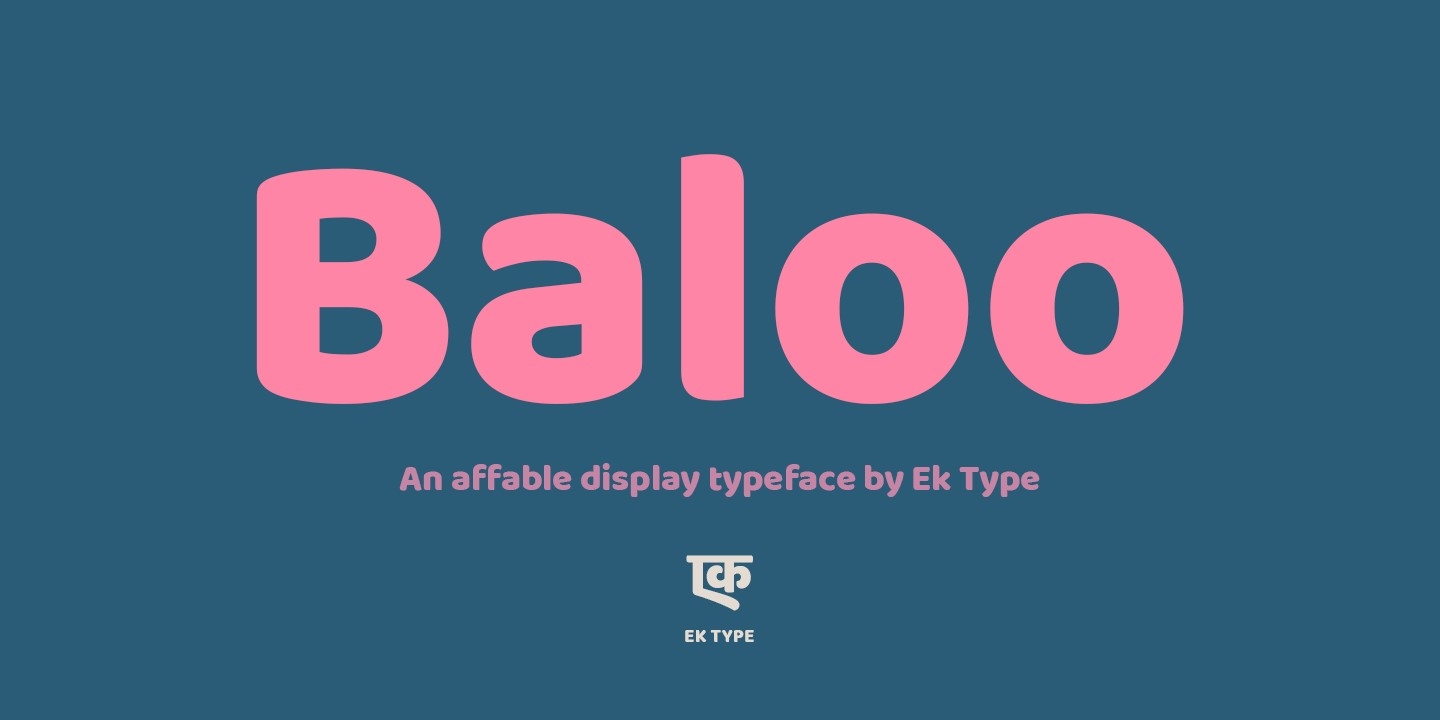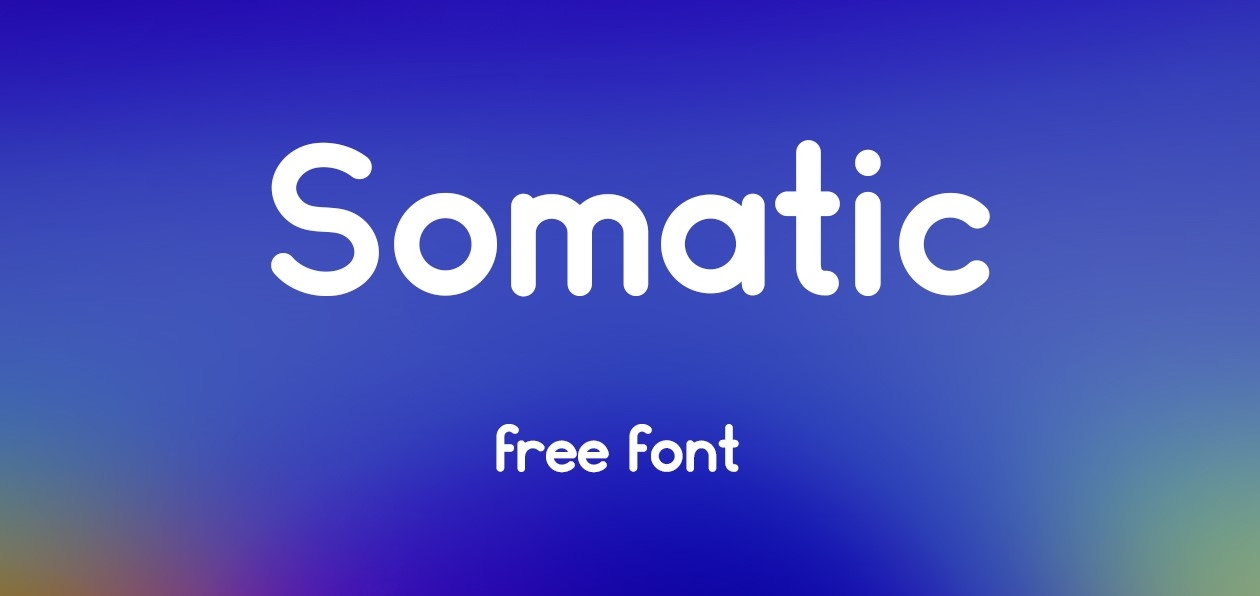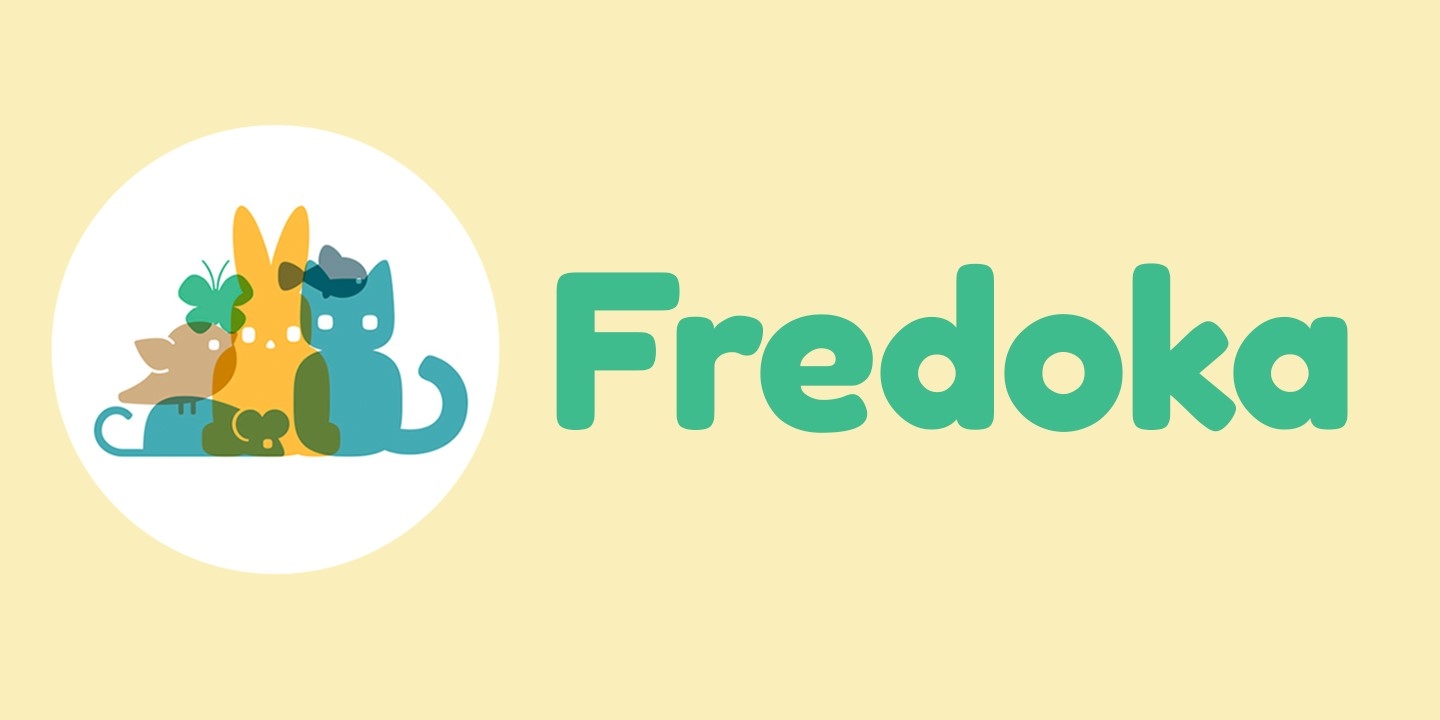
Tổng hợp TOP 15 font chữ tròn sinh động, sáng tạo, thiết kế đẹp mắt và ấn tượng
Các font chữ tròn với đường nét mềm mại, sinh động và sáng tạo luôn là lựa chọn hàng đầu của nhiều ấn phẩm thiết kế. Nhờ sở hữu vẻ đẹp gần gũi, vui tươi mà font chữ tròn luôn hút mắt người xem. Trong bài viết này, FPT Shop đã tổng hợp 15 font chữ tròn ấn tượng hiện nay, mời bạn cùng theo dõi nhé!
1. Baloo - Font chữ tròn miễn phí
Baloo nổi tiếng là một trong những font chữ tròn đẹp nhất dành cho dân thiết kế. Điểm thu hút của Baloo chính là những nét chữ tròn đáng yêu, ấn tượng với nhiều font family khác nhau, đáp ứng mọi nhu cầu sáng tạo.
Không chỉ được ưa chuộng tại Việt Nam, Baloo còn được sử dụng rộng rãi trên toàn thế giới. Font chữ này hỗ trợ đa dạng ngôn ngữ, bao gồm cả tiếng Việt và cho phép miễn phí sử dụng. Bạn có thể tải font Baloo ngay để thỏa sức sáng tạo mà không sợ bị lỗi font.
Baloo thích hợp với nhiều dự án thiết kế từ đơn giản đến phức tạp, chẳng hạn như: poster, logo, banner, website, danh thiếp, thiệp mời, bìa sách, bài đăng trên các phương tiện truyền thông xã hội và hơn thế nữa.
2. Somatic - Font chữ tròn hiện đại
Font chữ Somatic thu hút người dùng bởi những đường nét tròn trịa, mềm mại, tạo cảm giác vui tươi và đáng yêu. Đặc biệt, khi kết hợp với hiệu ứng gradient, Somatic càng trở nên nổi bật và ấn tượng hơn.
Nếu để ý kỹ hơn, bạn sẽ thấy Somatic sở hữu phong cách tương đồng với font chữ mà thương hiệu Apple sử dụng trong các sự kiện ra mắt sản phẩm đình đám.
Somatic sẽ là lựa chọn tuyệt vời cho những ai yêu thích phong cách trẻ trung, hiện đại và muốn tạo điểm nhấn ấn tượng cho thiết kế của mình. Hiện tại Somatic đang phát hành miễn phí cho tất cả người dùng và được đông đảo designer tin tưởng lựa chọn.
3. Fredoka - Font chữ tròn đẹp
Font chữ Fredoka thu hút bởi những đường nét bo tròn mềm mại, tạo cảm giác nhẹ nhàng và thanh thoát. Tuy là font chữ tròn nhưng Fredoka không quá to ngang nên dễ đọc, có khả năng hiển thị tốt và dễ dàng ứng dụng trong thiết kế.
Font Fredoka được nhiều designer ưa chuộng sử dụng cho các thiết kế trên website, phần mềm và các nền tảng trực tuyến. Font chữ này có thể tải về miễn phí từ Google Fonts.
4. Softa - Font chữ béo ngộ nghĩnh 3D
Được lấy cảm hứng từ những viên kẹo marshmallow bông xốp nên font chữ Softa sở hữu đường nét tròn trịa, mềm mại, kết hợp với hiệu ứng 3D độc đáo mang đến cảm giác vui tươi và tinh nghịch. Font chữ này cũng được tích hợp sẵn hiệu ứng đổ bóng mặc định cực kỳ thu hút và bắt mắt.
Softa thích hợp với các thiết kế mang tính sáng tạo như: logo, banner, poster, thiệp chúc mừng,... Đồng thời, font chữ cũng hỗ trợ nhiều định dạng khác nhau và tương thích với các phần mềm thiết kế. Bạn có thể tải và sử dụng font chữ Softa miễn phí cho mục đích cá nhân.
5. Yikes - Font chữ tròn tinh nghịch
Font chữ Yikes là một lựa chọn tuyệt vời cho những kiểu thiết kế mới lạ, tinh nghịch và ngộ nghĩnh. Với các đường nét tròn trịa và mềm mại, Yikes mang đến cảm giác thân thiện và dễ thương. Ngoài ra, font chữ Yikes cũng được thiết kế với độ phân giải cao, hiển thị sắc nét và đẹp mắt trên mọi thiết bị.
Font chữ Yikes đang được phát hành hoàn toàn miễn phí, cho phép người dùng sử dụng thoải mái trong các dự án cá nhân và thương mại. Hiện tại, Yikes đã được Việt hóa 100% nên bạn có thể tha hồ sử dụng mà không sợ bị lỗi font.
6. Earth Days Swash - Font chữ tròn béo hoa lá cành
Earth Days Swash là font chữ tròn béo mang đậm phong cách thiên nhiên với các họa tiết hoa lá cành ẩn chứa trong từng chữ cái. Font chữ này là lựa chọn hoàn hảo cho các thiết kế hướng đến trẻ em, các ấn phẩm về môi trường hoặc bất kỳ dự án nào muốn mang đến cảm giác tươi mới, gần gũi với thiên nhiên.
Earth Days Swash hỗ trợ nhiều ngôn ngữ và dễ dàng cài đặt trên các phần mềm thiết kế phổ biến. Đặc biệt, font chữ này đã được Việt hóa nên bạn có thể thoải mái sử dụng mà không lo lỗi font.
Tuy nhiên, bạn cần lưu ý font chữ này chỉ được sử dụng miễn phí cho mục đích cá nhân. Nếu muốn sử dụng cho mục đích thương mại thì bạn cần mua bản quyền gốc từ tác giả.
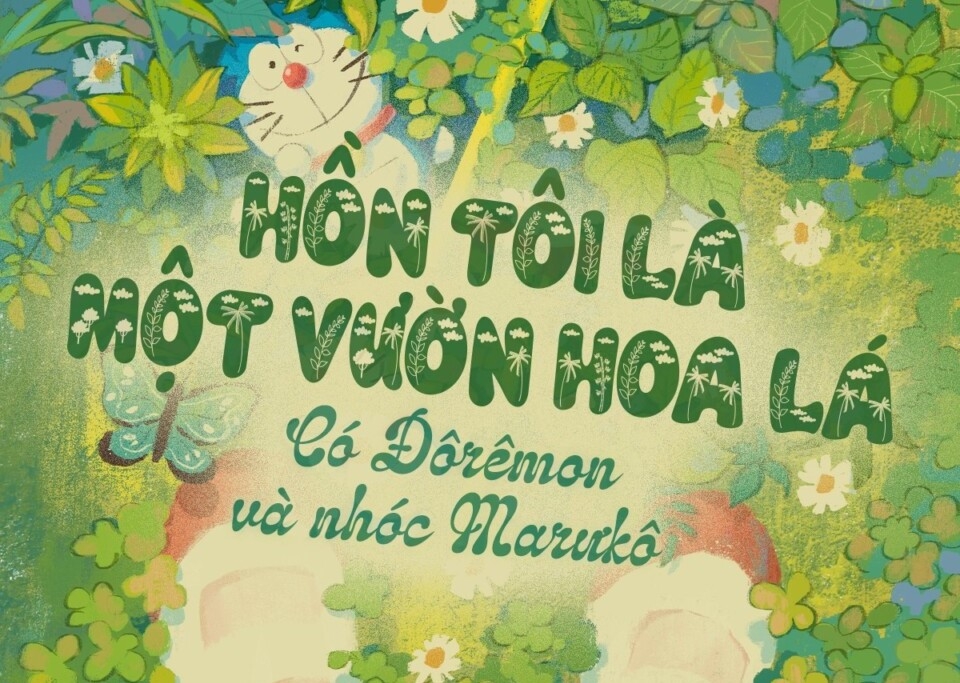
7. Alba Matter - Font chữ tròn vừa hoài cổ, vừa hiện đại
Alba Matter là font chữ tròn sở hữu vẻ đẹp hoài cổ xen lẫn hiện đại. Font chữ này đem lại cảm giác mộc mạc nhưng vẫn đầy tinh tế, phù hợp với các thiết kế mang phong cách vintage, retro hoặc muốn tạo điểm nhấn độc đáo.
Font Alba Matter đã được Việt hóa để người dùng có thể sử dụng tiếng Việt trong thiết kế một cách dễ dàng. Font này vô cùng lý tưởng cho các mẫu logo, poster cho quán ăn, tiệm cà phê, đồ thủ công, du lịch,...
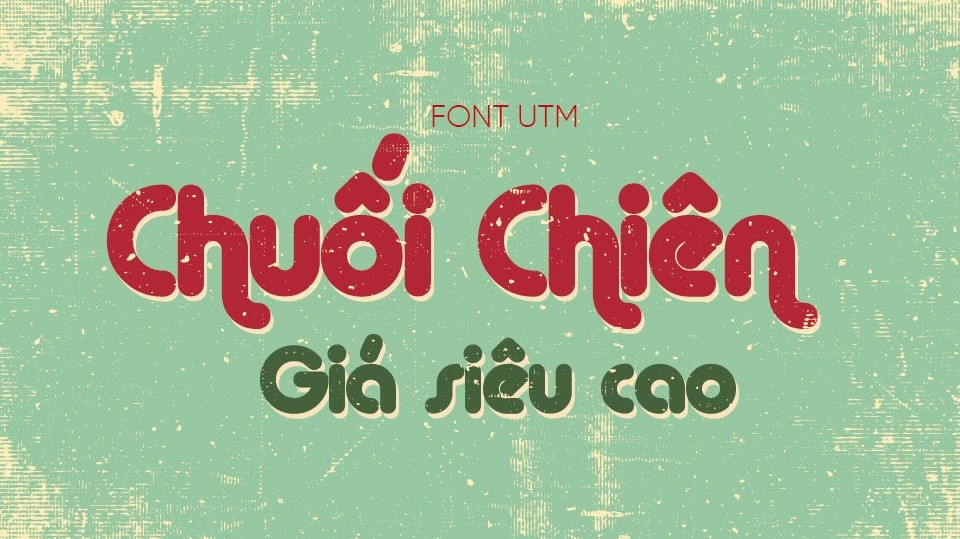
8. Kaige - Font chữ tròn hiện đại
Kaige là font chữ tròn sở hữu đường nét độc đáo, có độ dày lớn và khoảng cách giữa các ký tự rộng rãi. Font chữ này mang đến sự sang trọng, tinh tế và hòa hợp cho các mẫu thiết kế mang phong cách hiện đại. Nếu là một người thiết kế đồ họa chuyên nghiệp, nhất định bạn không nên bỏ qua font Kaige.
9. Mother - Font chữ tròn béo cổ điển
Mother là một font chữ tròn béo mang hơi hướng cổ điển và hoài niệm. Font chữ này đem lại cảm giác mộc mạc, giản dị nhưng vẫn đầy thu hút, phù hợp với những thiết kế mang phong cách hoài cổ vintage, retro hoặc thập niên 80.
Nhìn thoáng qua, bạn sẽ cảm thấy font chữ Mother có nét tương đồng với những biển hiệu cửa hàng của thập niên cũ khi còn viết bằng tay. Đặc biệt, Mother đã được Việt hóa 100% nên bạn có thể tha hồ sáng tạo với những thiết kế của mình mà không lo bị lỗi font.
10. Koni - Font chữ bo tròn đẹp
Font chữ Koni (hay còn được gọi là font chữ Kỳ Lân) được nhiều người ưa chuộng bởi vẻ đẹp mềm mại, tinh tế và không kém phần độc đáo. Đường nét của font Koni được bo tròn uyển chuyển giúp mang đến cảm giác nhẹ nhàng, thanh thoát và sang trọng. Vì vậy, Koni rất phù hợp để sử dụng trong các thiết kế chất lượng cao và đòi hỏi sự hài hòa trong từng chi tiết. Ngoài ra, font chữ Koni cũng đã được Việt hóa nên bạn có thể thoải mái tải về để sử dụng cho các thiết kế có chữ viết tiếng Việt.
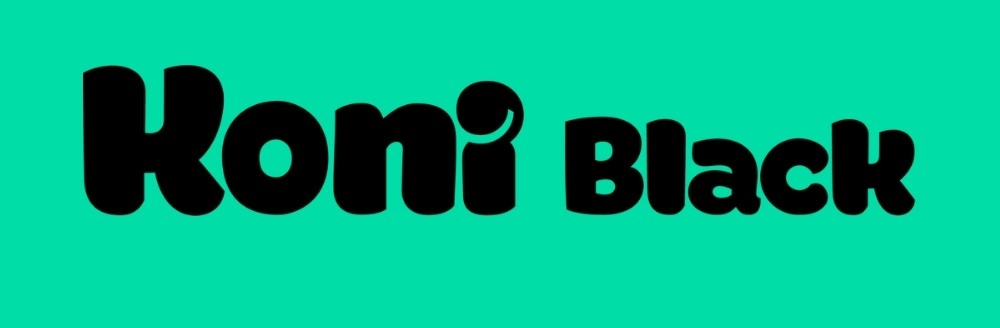
11. Mijas - Font chữ tròn đáng yêu
Mijas là sự kết hợp độc đáo giữa nét vuông và nét tròn, mang đến cảm giác mới lạ, vui nhộn và đáng yêu. Font chữ này đặc biệt phù hợp với những thiết kế hướng đến trẻ em hoặc các sản phẩm mang tính giải trí.
Font chữ Mijas đã được Việt hóa 100% với các ký tự hiển thị chính xác và đẹp mắt nên bạn có thể thoải mái sử dụng tiếng Việt trong thiết kế mà không lo bị lỗi.
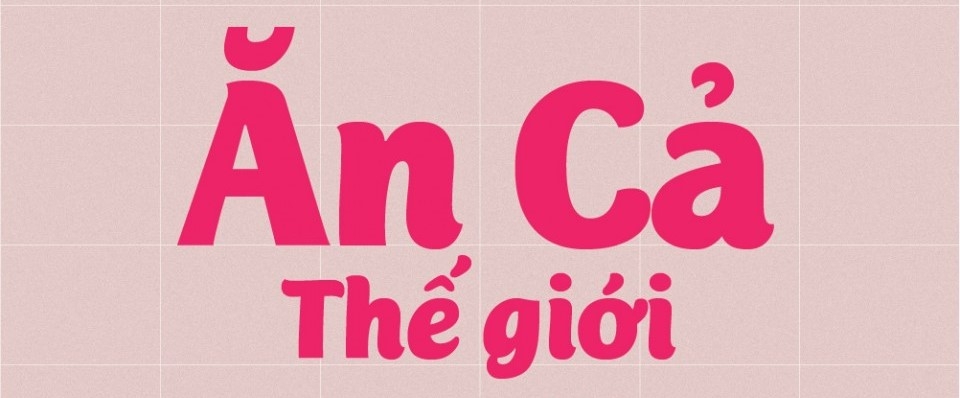
12. Pony - Font chữ tròn mập tinh nghịch
Pony là một font chữ sans-serif tròn mập sở hữu đường nét mềm mại, đáng yêu và tinh nghịch. Font chữ này mang đến cảm giác vui tươi, hồn nhiên và thu hút. Vì thế, Pony rất thích hợp với những thiết kế liên quan đến trẻ em, đồ chơi hoặc giáo dục. Font Pony đã được Việt hóa nên bạn có thể thỏa sức sáng tạo mà không sợ bị lỗi.
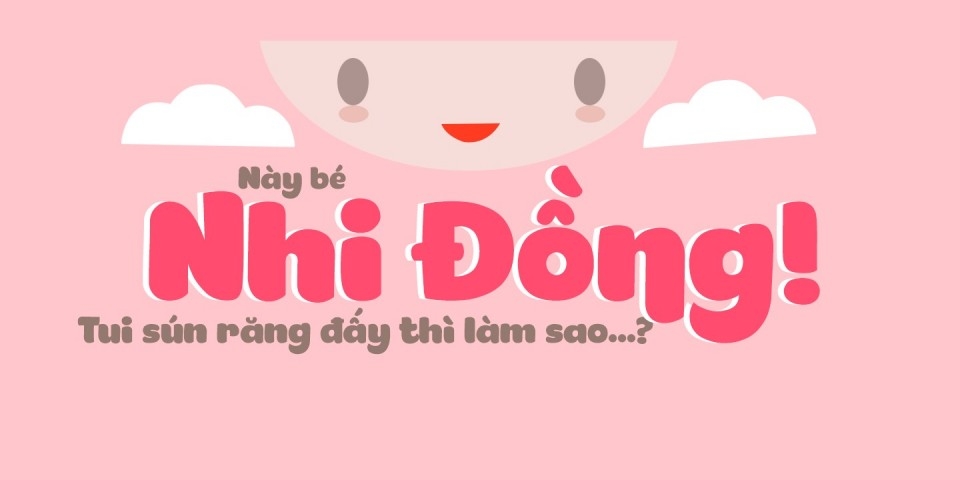
13. UTM Cooper - Font chữ tròn mập độc đáo
UTM Cooper là một font chữ serif mập tròn với nét đẹp độc đáo, tinh tế. Font chữ này sở hữu vẻ đẹp hiện đại, thu hút và đặc biệt phù hợp với những mẫu thiết kế cho nhà hàng, quán ăn, siêu thị, blog ẩm thực,...
Hiện tại, UTM Cooper đã được Việt hóa và sử dụng bảng mã Unicode nên bạn không cần lo lắng về vấn đề lỗi font. Bạn có thể tải font về máy và sử dụng miễn phí cho mục đích cá nhân. Nếu muốn sử dụng với mục đích thương mại, tốt nhất bạn nên mua bản quyền gốc từ tác giả.
14. ARCO - Font chữ tròn đẹp, đơn giản
ACRO là cái tên phổ biến trong bộ font của những người thiết kế đồ họa bởi chất lượng tốt, đẹp và có thể áp dụng cho nhiều phong cách khác nhau. Font ARCO sở hữu đường nét đơn giản được bo tròn mềm mại, mang đến sự thanh lịch và hiện đại cho thiết kế. Font chữ này đã được Việt hóa hoàn chỉnh, giúp người dùng Việt có thể sáng tạo dễ dàng.
15. Cadena - Font chữ tròn dễ thương
Cadena là một font chữ tròn có độ dày lớn với các đường nét mềm mại, uyển chuyển. Font chữ này mang lại cảm giác thân thiện, vui tươi và bay bổng, phù hợp với những thiết kế sáng tạo mang hơi hướng nữ tính hoặc trẻ em.
Cadena đã được Việt hóa 100% với các ký tự hiển thị trực tiếp qua Unicode mà không cần tinh chỉnh. Bên cạnh đó, font chữ Cadena cũng được phát hành miễn phí, bạn có thể tải về và sử dụng cho các dự án cá nhân cũng như thương mại.
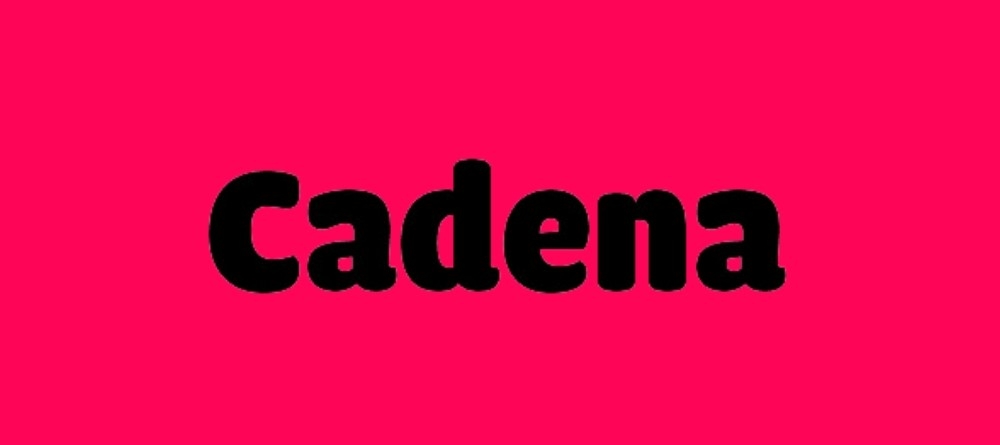
Cách tải font chữ tròn nhanh chóng
Bạn có thể tải về toàn bộ font chữ tròn đẹp tại đây: Font chữ tròn
Lời kết
Vậy là FPT Shop đã chia sẻ đến bạn TOP 15 font chữ tròn đẹp với đa dạng các phong cách khác nhau: tối giản, hiện đại, cổ điển, dễ thương, tinh nghịch,... Hy vọng bạn sẽ lựa chọn được font chữ phù hợp với thiết kế của mình và thỏa sức sáng tạo nhé!